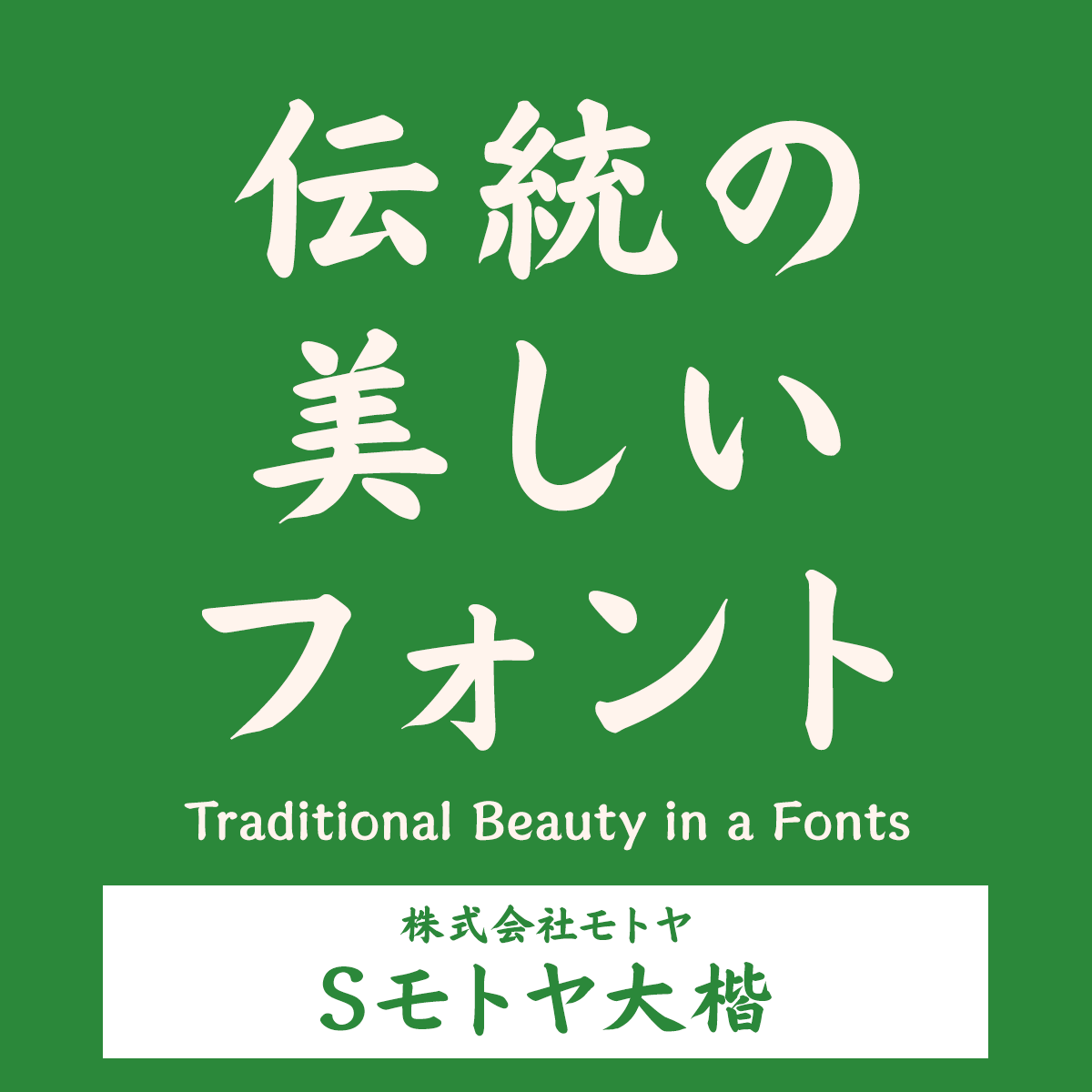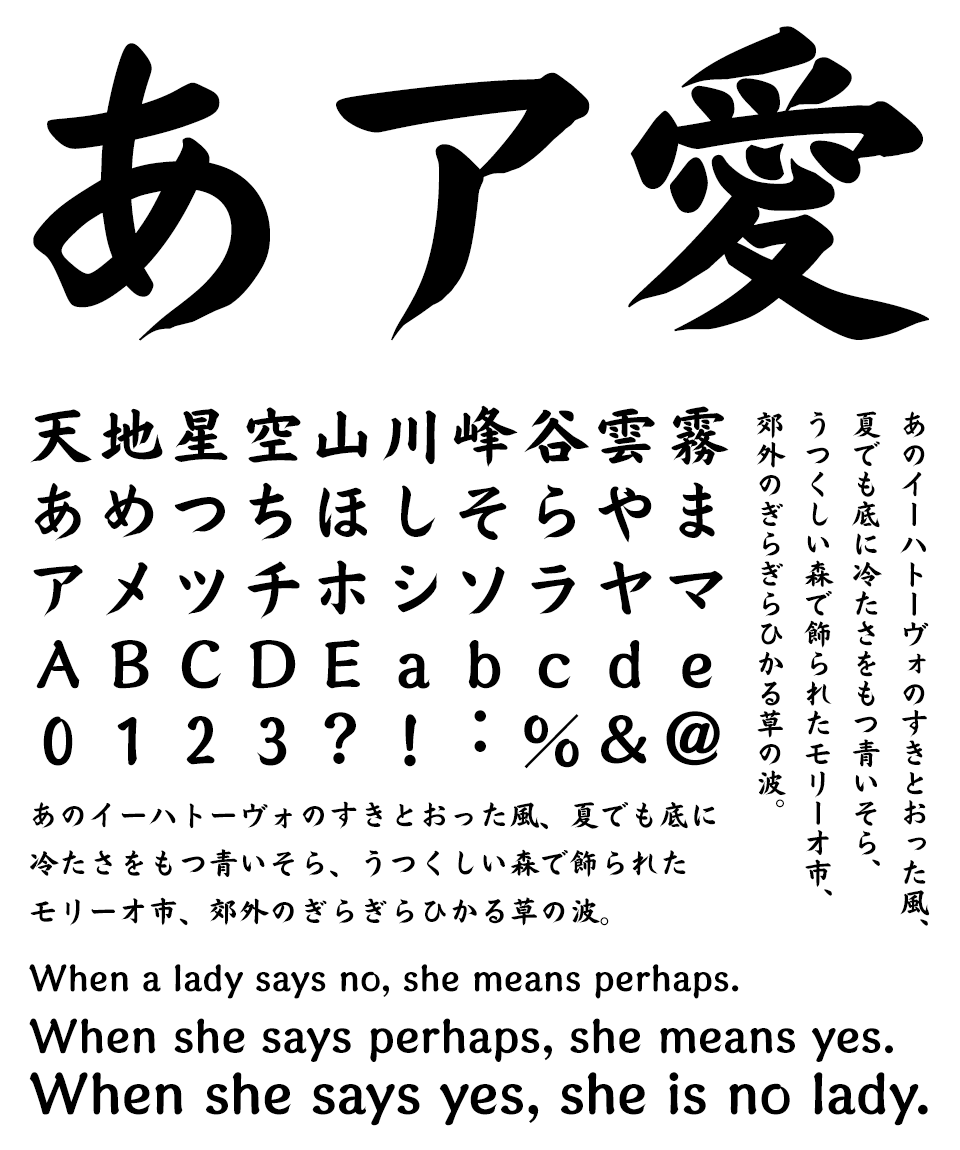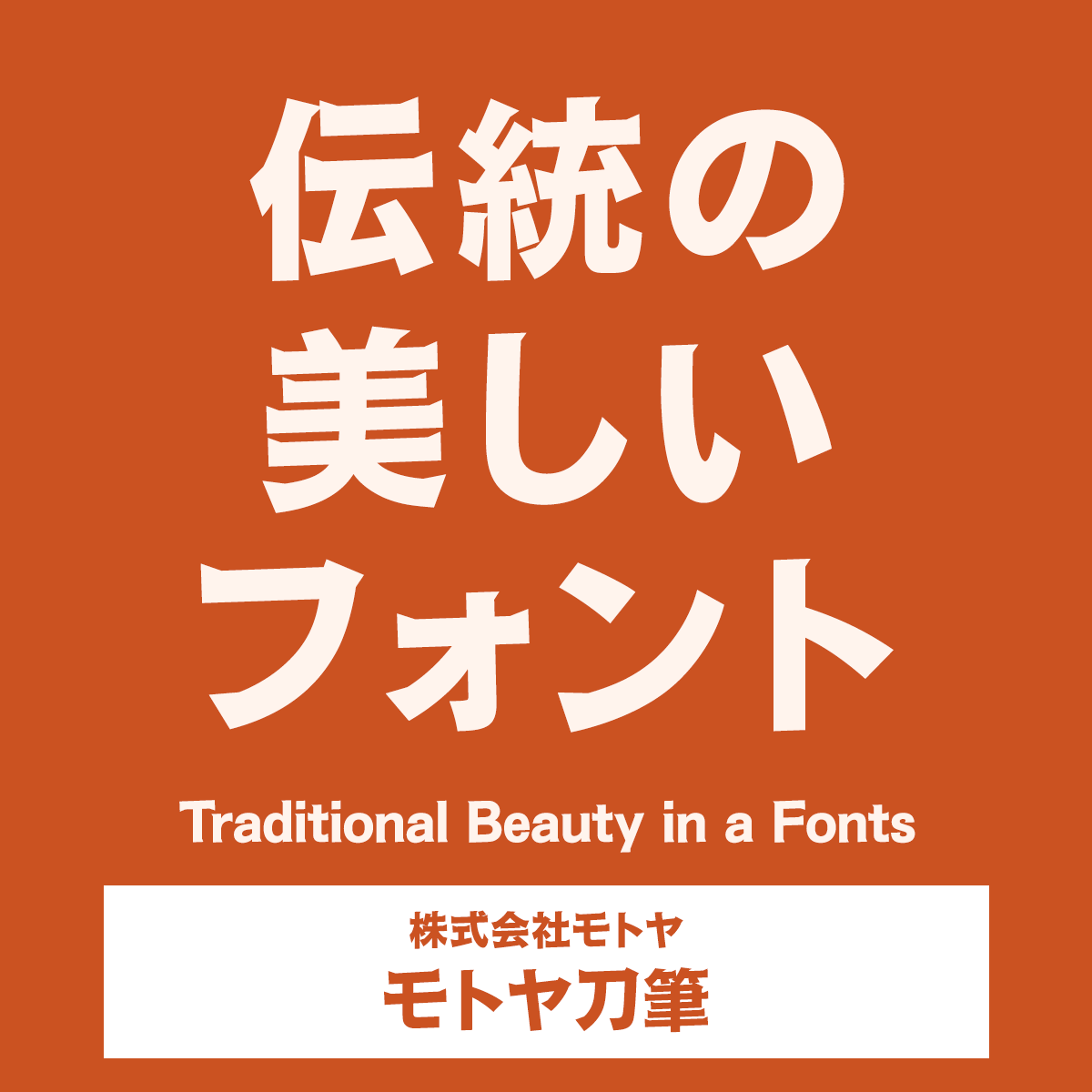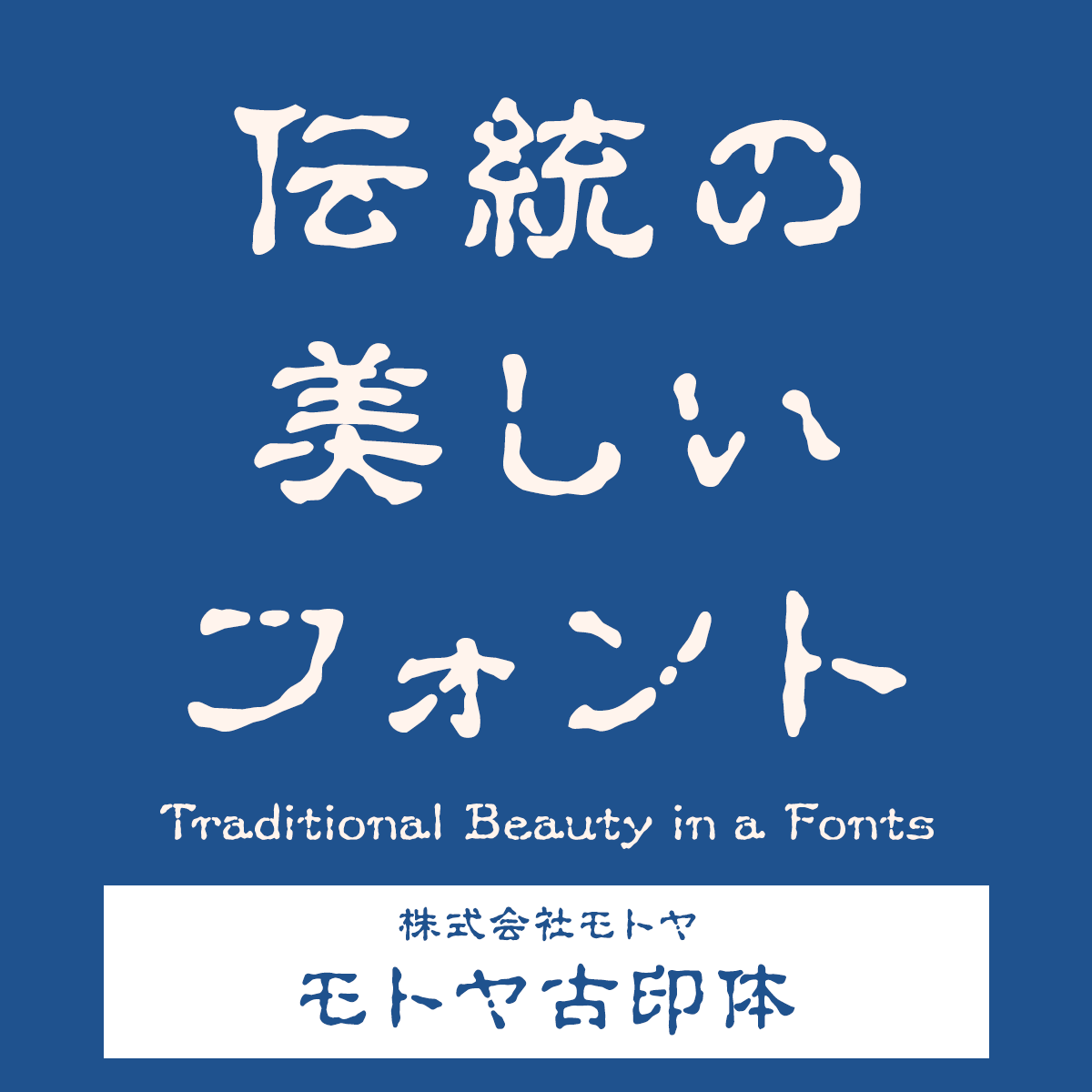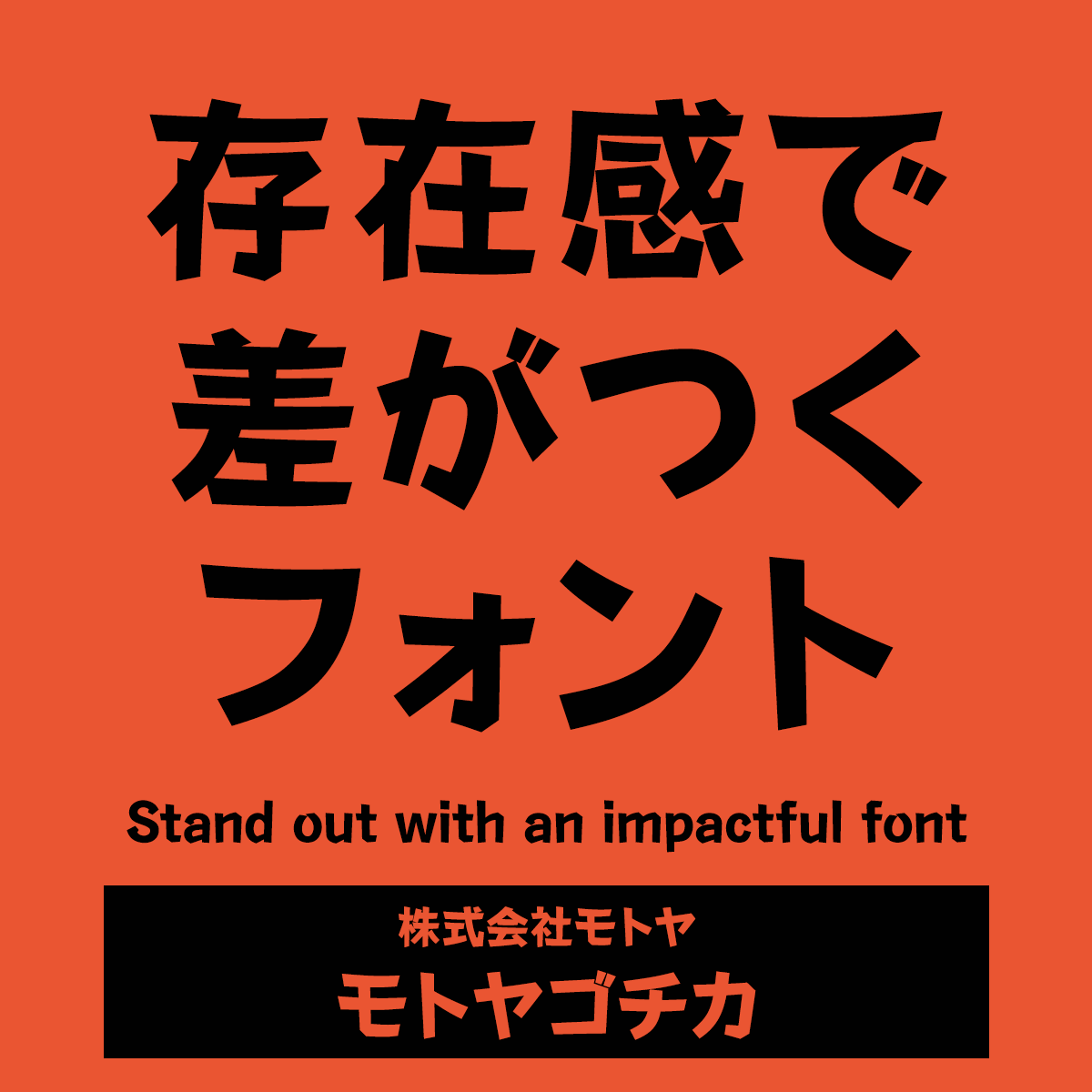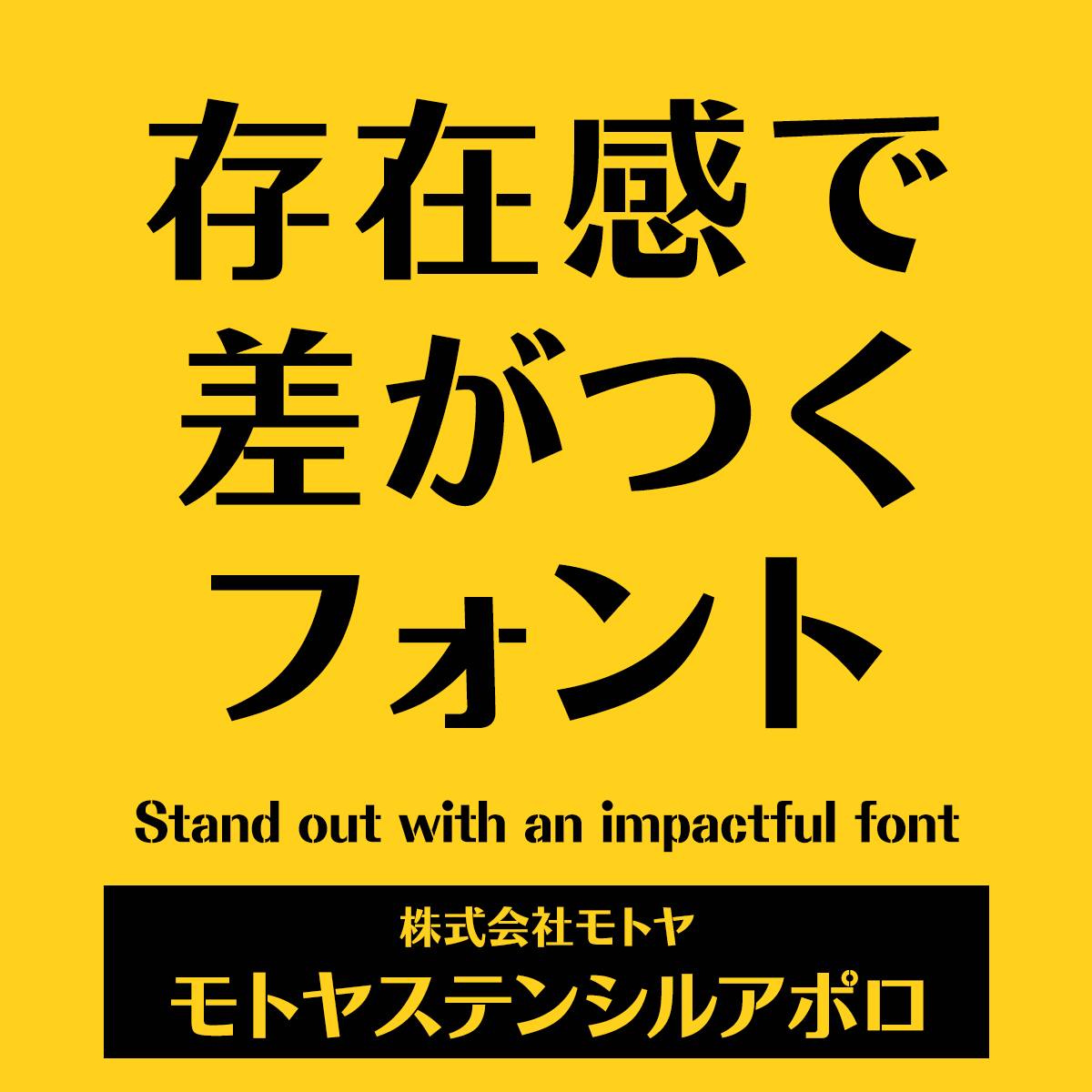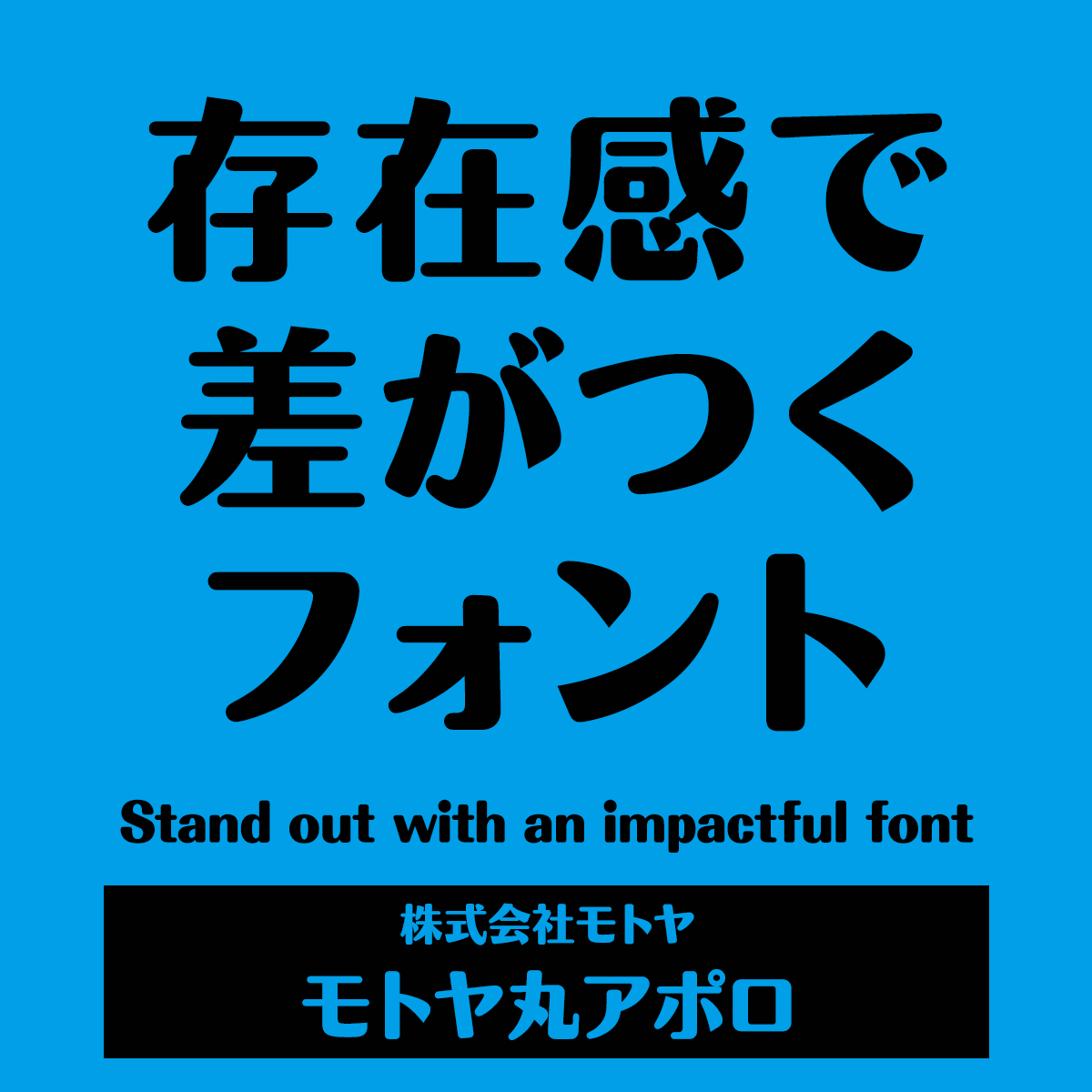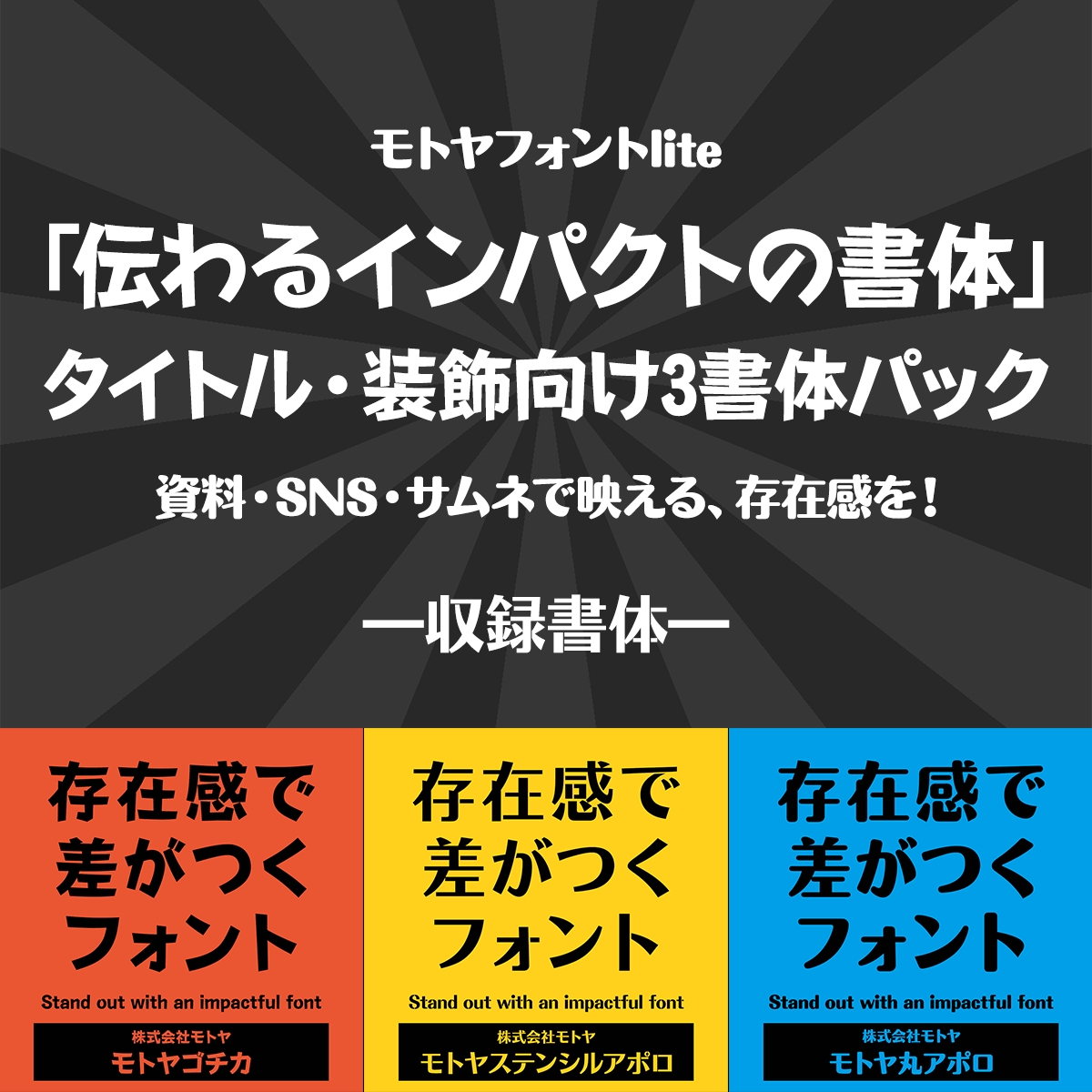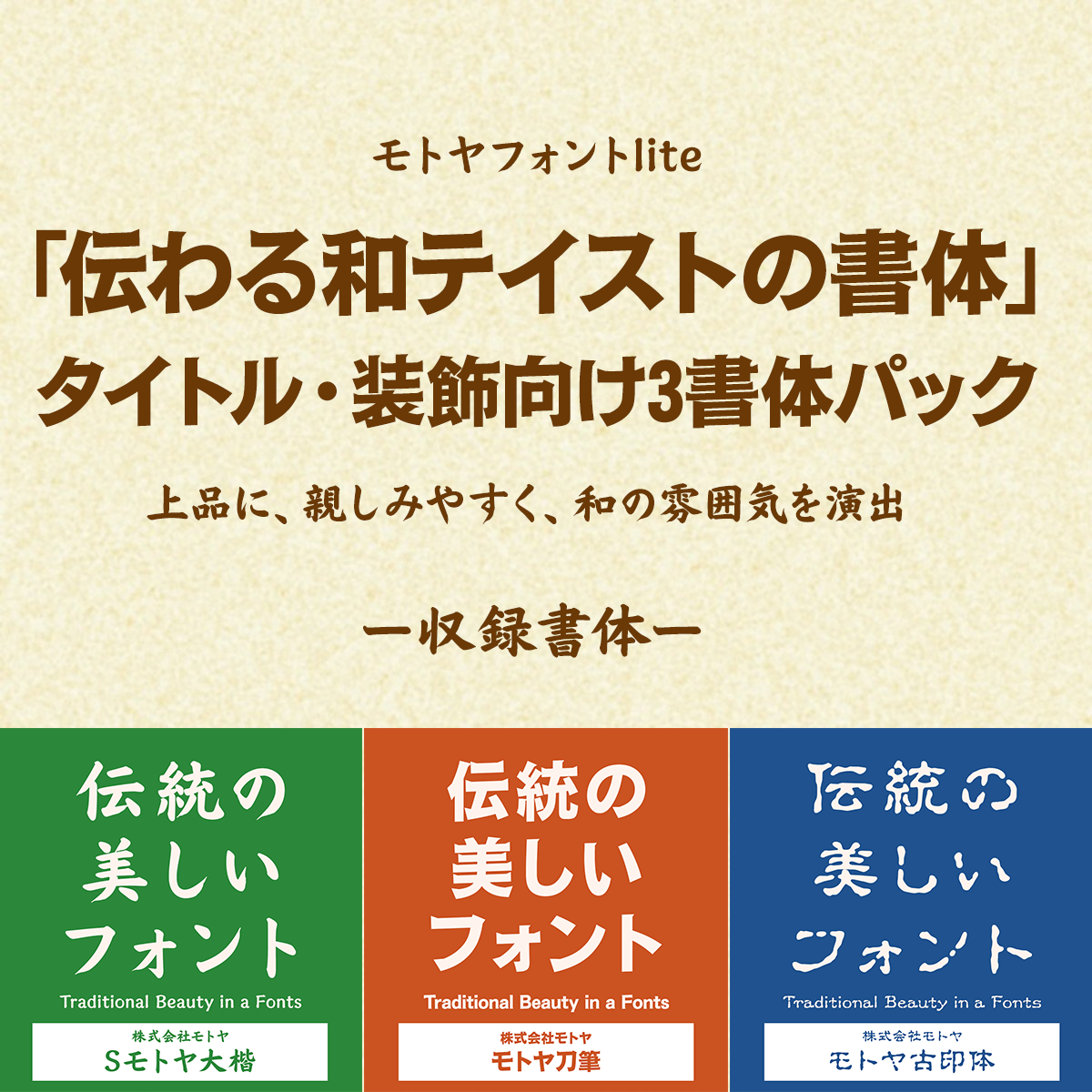
モトヤフォントlite3書体セット
資料もSNS投稿もサムネも“伝わらない”を卒業する。
モトヤフォントlite タイトル・装飾向け3書体パック
「伝えたいのに、なんだかパッとしない。」
SNSの投稿、営業資料、チラシやサムネイル──日々、言葉を届けるためにデザインをする場面は増えています。でも、フォント選びがしっくりこないまま、毎回なんとなくで済ませてしまっていませんか?
モトヤフォントliteの「タイトル・装飾向け3書体パック」は、そんな“伝わらない”お悩みにこたえるために生まれました。
文字の印象を活かして、あなたの発信をもっと魅力的に。「和の雰囲気で上品に見せたい」「SNSで埋もれず印象を残したい」── そんなニーズに応える、2つの厳選セットをご用意しました。
「伝わるインパクトの書体」は、資料・SNS・サムネで映える存在感を。「伝わる和テイストの書体」は、上品に、親しみやすく、和の雰囲気を演出。各3書体を厳選収録しました。
目立たない・伝わらない・チープに見える——その原因、フォントです。
こんな悩み、感じたことありませんか?
• 「SNS投稿が埋もれてしまって反応が少ない…」
• 「せっかく作った資料やチラシ、なんだか安っぽい気がする」
• 「タイトルに使えるフォントが見つからない」
• 「パワポの書体、どれも似たりよったりで個性が出せない」
• 「フォントに詳しくないから、毎回無難な書体にしてしまう」
資料や投稿、告知画像を自分で作る時、“伝えたいのに伝わらない”と感じることはありませんか?
それ、フォントの選び方で大きく変わります。
伝えたい“印象”に合わせて、フォントを選ぶだけ。モトヤフォントliteなら、誰でもプロ級の仕上がりに。
モトヤフォントlite「タイトル・装飾向け3書体パック」は、目的に合わせて選ぶだけで、誰でも印象的なデザインができるフォントセットです。
伝わるインパクトの書体」は、SNSやチラシ、営業資料など“目立たせたい”場面で活躍。
伝わる和テイストの書体」は、上品で落ち着いた印象を演出したい場面に。
どちらも、チープにならずに、伝えたい雰囲気をフォントでコントロールできます。「自分のデザインに自信がない」という方にも、安心してお使いいただける内容です。
モトヤフォントliteとは
伝統のフォントデザインで最先端のニーズに応えるモトヤフォント。
「伝わるインパクトの書体」タイトル・装飾向け3書体パック
収録書体 1モトヤゴチカ6 LiteN
モトヤゴチカ6 LiteN
収録書体 2モトヤステンシルアポロ6 LiteN
モトヤステンシルアポロ6 LiteN
収録書体 3モトヤ丸アポロ8 LiteN
モトヤ丸アポロ8 LiteN
「個性的なサムネで興味を引きたい」「インパクトのある資料にしたい」――そんな時にぴったりの3書体をセットにしました。モトヤゴチカ、モトヤステンシルアポロ、モトヤ丸アポロは、SNS投稿やYouTubeサムネイル、営業資料、チラシなどで見せたい言葉をしっかり際立たせます。カジュアルにもビジネスにも使いやすく、幅広い発信シーンに対応できる、実用性と表現力を兼ね備えた書体セットです。
「伝わる和テイストの書体」タイトル・装飾向け3書体パック
収録書体 1Sモトヤ大楷5 LiteN
Sモトヤ大楷5 LiteN
収録書体 2モトヤ刀筆6 LiteN
モトヤ刀筆6 LiteN
収録書体 3モトヤ古印体5 LiteN
モトヤ古印体5 LiteN
「落ち着いた雰囲気にしたい」「和の空気感を出したい」――そんな時にぴったりの3書体をセットにしました。Sモトヤ大楷、モトヤ刀筆、モトヤ古印体は、それぞれ異なる個性を持ちながらも、共通して“日本らしい情緒”や“あたたかみ”を感じさせる書体です。和食店や旅館、観光イベントのチラシ、商品パッケージ、年賀状、同人誌のタイトルなど、和テイストを必要とするあらゆる場面に自然に馴染み、雰囲気づくりをサポートします。
使用例
チラシ・フライヤー
使用書体:モトヤ丸アポロ8 LiteN、Sモトヤ大楷5 LiteN、モトヤ古印体5 LiteN、モトヤステンシルアポロ6 LiteN、モトヤゴチカ6 LiteN
SNS投稿
使用書体:Sモトヤ大楷5 LiteN (左上)、モトヤゴチカ6 LiteN (右上)、モトヤステンシルアポロ6 LiteN (左下)、モトヤ丸アポロ8 LiteN (右下)
動画・サムネイル
使用書体:モトヤゴチカ6 LiteN、モトヤ丸アポロ8 LiteN、モトヤ刀筆6 LiteN、Sモトヤ大楷5 LiteN、モトヤステンシルアポロ6 LiteN、モトヤ古印体5 LiteN
収録書体のご紹介
「伝わるインパクトの書体」タイトル・装飾向け3書体パック
収録書体 1モトヤゴチカ6 LiteN
モトヤゴチカ6 LiteN イメージ画像 モトヤゴチカ6 LiteN 文字見本
モトヤゴチカ6 LiteN
ゴシック体をベースとして横線やハライに筆文字の勢いを表現することで、躍動感とチカラ強さを感じさせる書体です。
収録書体 2モトヤステンシルアポロ6 LiteN
モトヤステンシルアポロ6 LiteN イメージ画像 モトヤステンシルアポロ6 LiteN 文字見本
モトヤステンシルアポロ6 LiteN
モトヤアポロの清涼感を残しつつ、ステンシル(図柄や模様等をくりぬいた型紙を用いて行う手法)処理を施した書体です。
収録書体 3モトヤ丸アポロ8 LiteN
モトヤ丸アポロ8 LiteN イメージ画像 モトヤ丸アポロ8 LiteN 文字見本
モトヤ丸アポロ8 LiteN
モトヤアポロのハネ先や角を丸め、また部分的に角を残した柔らかくシャープな印象の書体です。